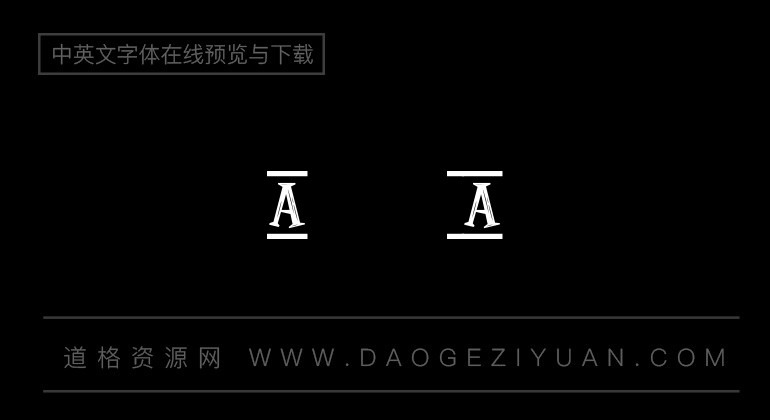
Ancient Ad
Ancient Ad 是一种古代风格的字体,它的设计灵感来源于古代的广告和招贴。这种字体的特点是笔画清晰,线条粗壮,有一种历史感和古老感。Ancient Ad 可以用于设计古代风格的标志、海报、广告和书籍题字等场合。这种字体也常用于游戏、电影和电视作品的字幕和标志设计中,以营造出一种神秘、古老的气氛。
Ancient Ad是一款非常不错的手写艺术字体,具有很好的视觉感,适合于文化类的宣传设计、商业类品牌的广告和产品包装设计以及个性化文字排版等较多场景。